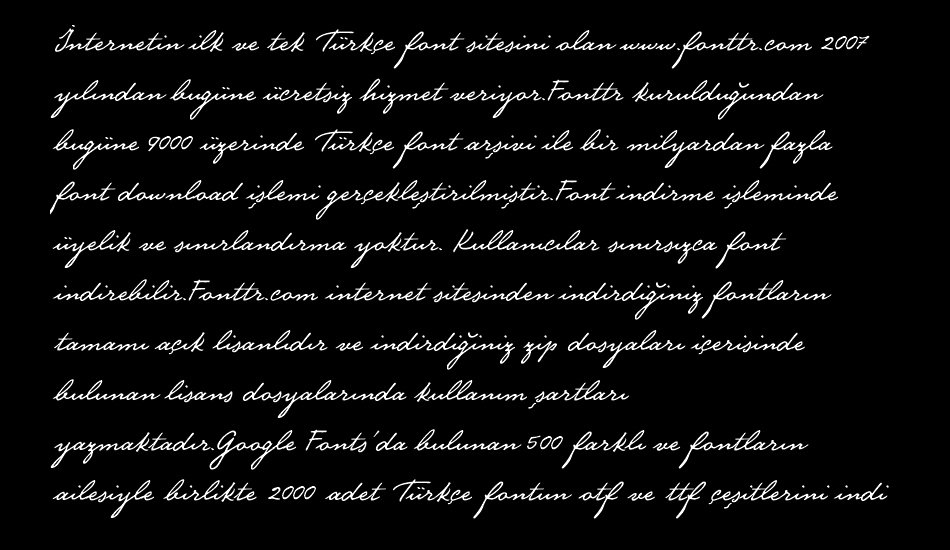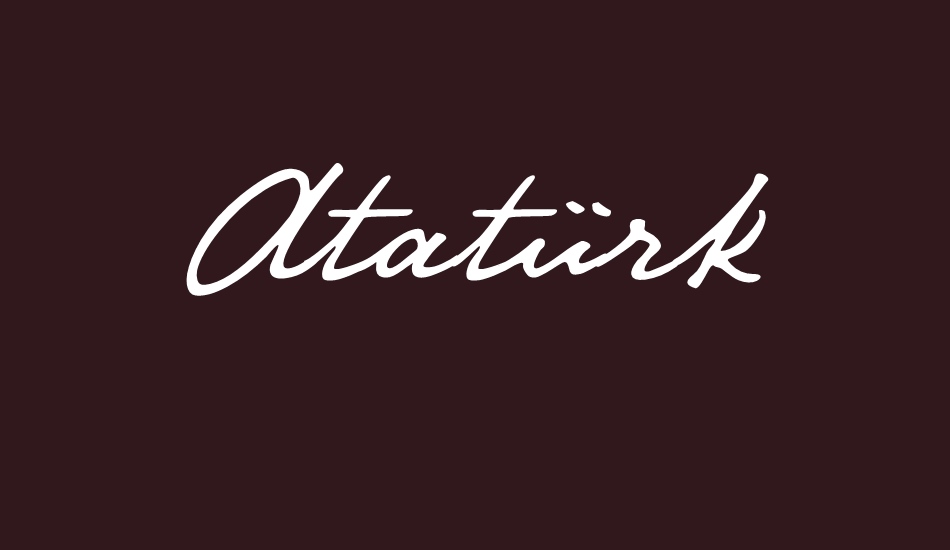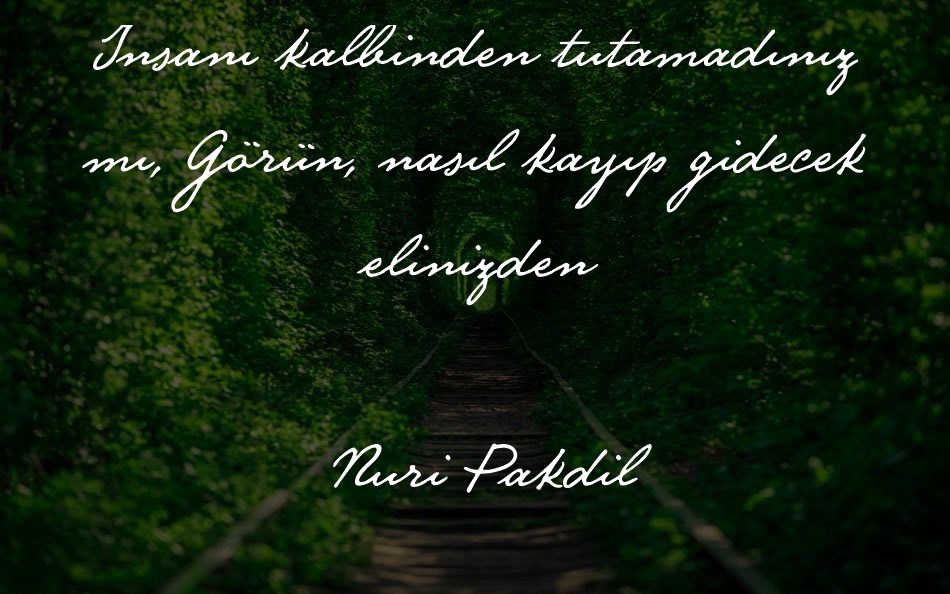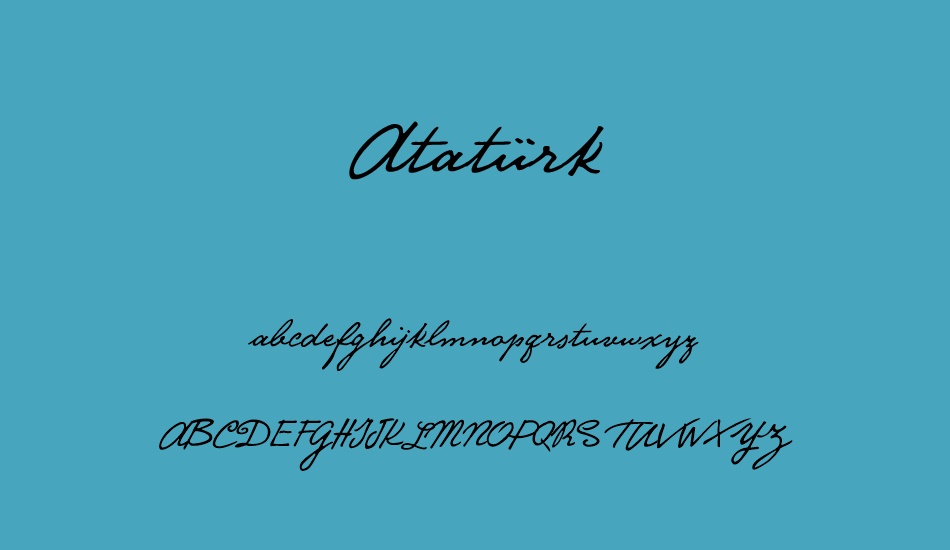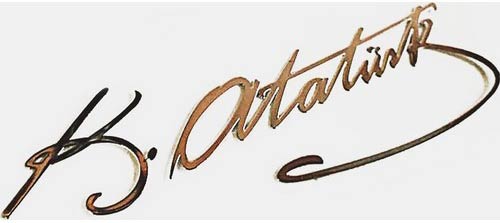
Atatürk imzası ve el yazısı font
Atatürk İmzası
K.Atatürk imzasında bulunan " K " harfi KAMAL kelimesinin kısaltmasıdır. İmzanın uzun yazılışı KAMAL ATATÜRK' tür.  https://sozluk.gov.tr/  isimli resmi sözlük web sitesinde kamal kelimesinin bir Türkçe karşılığı olmadığı anlaşılmaktadır. Kamal kelimesi Özbekçe, Kazakça ve İbranice sözlüklerde farklı anlamlara sahiptir.
Kemal Atatürk 1935 yılı Ocak ayından itibaren resmi yazışmalarında ki adını KAMAL Atatürk olarak kullanmaya başlamıştır. Atatürk ölümüne kadar Kamal ismini kullanmıştır. 993815 B nolu resmi kimliğine göre adı Kamal Atatürk'tür.
993815 B nolu, Kamal Atatürk'ün Nüfus Hüviyet Cüzdanı. (24.11.1934)
Atatürk imzası robert lisesinde ermeni asıllı bir öğretmen olan hagop vahram çerçiyan yaptırılmıştır. 1934 yılında Soyadı Kanunu’nun kabul edilmesiyle birlikte Mustafa Kemal’e Atatürk soyadı verildi” Ermeni Hagop vahram çerçiyan öğrencileri, Atatürk’e güzel bir imza numunesi armağan etme kararı alır. Karar öğrencileri tarafından Atatürk’ün hususi kalemi vasıtasıyla Boğaziçi’ndeki Bebek semti Komiserliği tarafından ermeni hagop vahram çerçiyan bildirildi.”  çerçiyan'ın kaligrafideki uzmanlığı, çerçiyan'dan bizzat 5 adet imza örneği istenmiştir. Atatürk imzası, çerçiyan 24 saat içerisinde 5 adet imzayı hazırlamıştır. Ermeni kaligrafin hazırladığı beş imzadan bir tanesi olan imza, günümüzde Atatürk imzası olarak bilinmektedir.
atatürk imzası
2012 yılında, Bursa merkezli Artikel’in kurucusu işadamı Murat Özbalcı, ABD’de bir yazılım firmasına Atatürk’ün imzasını ve orijinal el yazısının fontunu yaptırmıştır. Atatürk yazı fontu ve Atatürk imza indir. Mustafa Kemal imzası.
Atatürk font